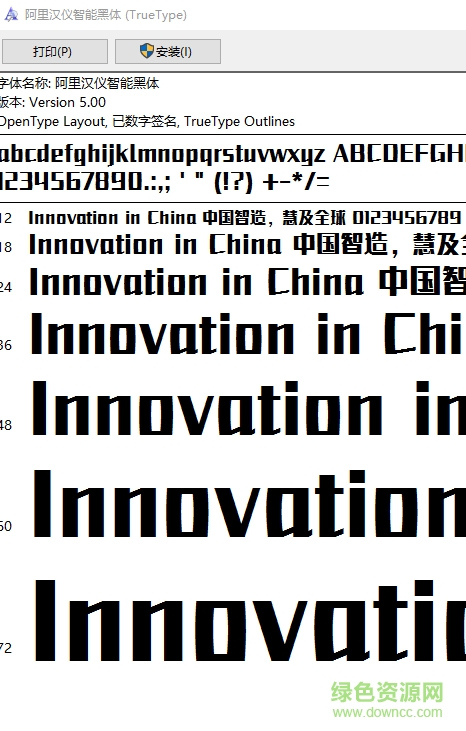
阿里漢儀智能黑體是首款應(yīng)用于電商行業(yè)的黑體軟件,該字體粗黑精細(xì)程度適中,辨識(shí)度很高,整體效果大方好看,還有更多類似字體歡迎來(lái)綠色資源網(wǎng)下載體驗(yàn)!
阿里漢儀智能黑體基于黑體的橫豎基本特征,加大橫豎粗細(xì)比例,字面飽滿填充整個(gè)內(nèi)框,讓字體更加醒目,視覺沖擊力極強(qiáng),能夠很好的與用戶對(duì)話,非常適用于電商類廣告設(shè)計(jì)。電商字體通用性極強(qiáng),適用于絕大多數(shù)品類的商品。智能黑體區(qū)別于常規(guī)黑體,剛中帶柔,筆畫的走勢(shì)上融入了手寫的方式,整體方正但又不失趣味,度量把握適中。
阿里漢儀智能黑體,字形由漢儀字庫(kù)的字體設(shè)計(jì)師黃珍元主創(chuàng)設(shè)計(jì),字庫(kù)產(chǎn)品協(xié)同阿里人機(jī)自然交互實(shí)驗(yàn)室,通過(guò)強(qiáng)大的計(jì)算能力自學(xué)生成。這款字體是基于阿里巴巴電商平臺(tái)應(yīng)用場(chǎng)景下產(chǎn)生的新分類字體 —— 電商字體。